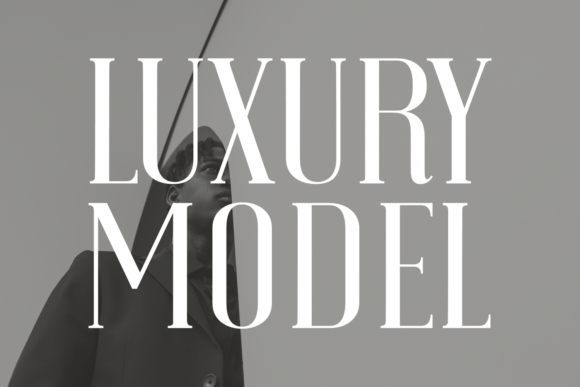
Luxury Model
Si vous recherchez des ressources de haute qualité comme Luxury Model, ce pack premium est un choix fantastique pour vos projets créatifs.
Conçu avec précision, Luxury Model offre des vecteurs nets, une typographie fluide et une licence commerciale pour une tranquillité d'esprit.
Que vous créiez des produits POD (impression à la demande), des invitations de mariage ou des visuels pour les réseaux sociaux, Luxury Model est un choix idéal.